Kalau diperhatikan, tampilan chat WhatsApp itu-itu saja. Font sama, gaya tulisan mirip semua, dan ujung-ujungnya cuma main bold atau italic. Lama-lama, chat terasa datar, apalagi kalau sering dipakai buat ngobrol panjang atau kirim pengumuman.
Padahal, di balik tampilan sederhananya, WhatsApp menyimpan banyak trik format yang jarang dipakai orang. Bukan fitur resmi yang kelihatan jelas, tapi kombinasi simbol dan karakter tertentu yang bisa mengubah kesan pesan secara drastis.
Buat yang Bosan Tampilan Standar? Cara Unlock Hidden Font dan Format Rahasia WhatsApp Selain Bold & Italic, format rahasia ini layak dicoba. Sekali terbiasa, chat standar bakal terasa terlalu polos.
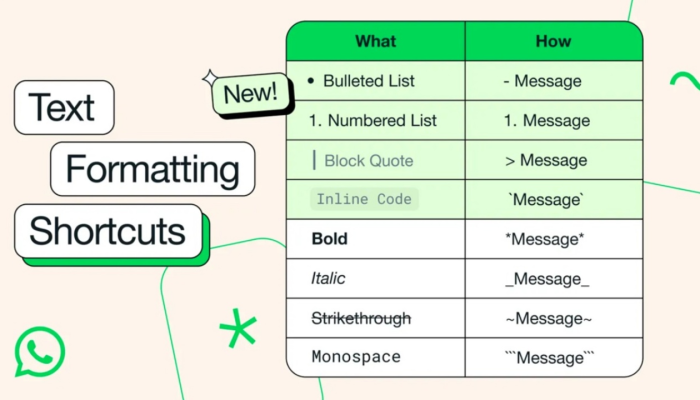
1. Gunakan Strikethrough untuk Efek “Coret Tapi Tetap Dibaca”
Format coret sering dipakai untuk bercanda, revisi, atau sindiran halus. Sayangnya, masih jarang dimanfaatkan.
Caranya cukup sederhana dengan menambahkan tanda tertentu di awal dan akhir teks. Hasilnya, tulisan akan tercoret rapi tanpa menghilangkan keterbacaan.
Efek ini cocok untuk:
Revisi pesan
Candaan internal
Penekanan konteks yang berubah
Secara visual, chat langsung terlihat lebih ekspresif.
2. Manfaatkan Monospace untuk Tampilan ala Kode atau Catatan Rahasia
Monospace memberi kesan teknis dan “dingin”. Font ini sering dipakai untuk kode, catatan sistem, atau pesan yang ingin terlihat beda sendiri.
Begitu diterapkan, teks akan tampil rata dan kaku, sangat kontras dengan chat biasa. Justru di situlah daya tariknya.
Format ini pas untuk detail teknis, password dummy, atau pesan yang ingin tampak eksklusif.
3. Kombinasikan Beberapa Format dalam Satu Kalimat
WhatsApp memungkinkan beberapa format aktif dalam satu pesan. Bold, italic, coret, dan monospace bisa digabung dengan urutan yang tepat.
Hasilnya, pesan terlihat lebih dinamis dan tidak monoton. Pembaca pun lebih mudah menangkap bagian penting.
Namun, penggunaan sebaiknya tetap wajar. Terlalu banyak format justru bikin pesan sulit dibaca.
4. Gunakan Spasi dan Baris Kosong untuk Ilusi Layout
Meski WhatsApp tidak punya fitur alignment, spasi dan baris kosong bisa dimanfaatkan. Dengan sedikit pengaturan jarak, pesan bisa terlihat lebih rapi dan “bernapas”.
Trik ini sering dipakai untuk:
- Pengumuman grup
- Daftar poin penting
- Pesan panjang agar tidak melelahkan mata
Secara tidak langsung, format visual pesan ikut berubah.
5. Sisipkan Simbol dan Karakter Unik untuk Gaya Font Berbeda
Beberapa karakter Unicode bisa memberi kesan font berbeda meski bukan font asli WhatsApp. Efeknya mirip gaya tulisan unik.
Karakter seperti garis, titik tengah, atau simbol tertentu bisa memperkuat kesan visual. Pesan jadi terasa lebih personal dan tidak generik.
Gunakan secukupnya agar tetap terbaca di semua perangkat.
6. Pakai Line Break untuk Penekanan Emosi
Kadang, bukan font yang bikin pesan kuat, tapi jeda. Baris baru yang ditempatkan dengan tepat bisa memberi tekanan emosional.
Satu kalimat pendek di baris terpisah sering terasa lebih “kena”. Teknik ini banyak dipakai tanpa sadar, tapi efeknya nyata.
Pesan jadi lebih hidup tanpa perlu format ribet.
Simpan Template Format Favorit untuk Dipakai Ulang
Kalau sudah menemukan gaya yang cocok, template bisa disimpan. Tinggal salin, ubah isi, lalu kirim.
Cara ini menghemat waktu dan menjaga konsistensi gaya. Cocok untuk admin grup, kerjaan, atau broadcast rutin.
WhatsApp memang sederhana, tapi bisa dibuat jauh lebih fleksibel.
WhatsApp mungkin terlihat minimalis, tapi bukan berarti membosankan. Di balik tampilan standar, ada banyak format tersembunyi yang bisa dimanfaatkan untuk membuat chat lebih ekspresif dan berkarakter.
Strikethrough, monospace, kombinasi format, hingga permainan spasi bisa mengubah cara pesan dibaca dan dirasakan. Tidak perlu aplikasi tambahan, tidak perlu ribet, hanya butuh sedikit eksplorasi. Kalau selama ini chat terasa terlalu datar, mungkin bukan karena obrolannya. Bisa jadi karena formatnya belum dimaksimalkan. Coba satu trik saja hari ini, dan rasakan sendiri bedanya.